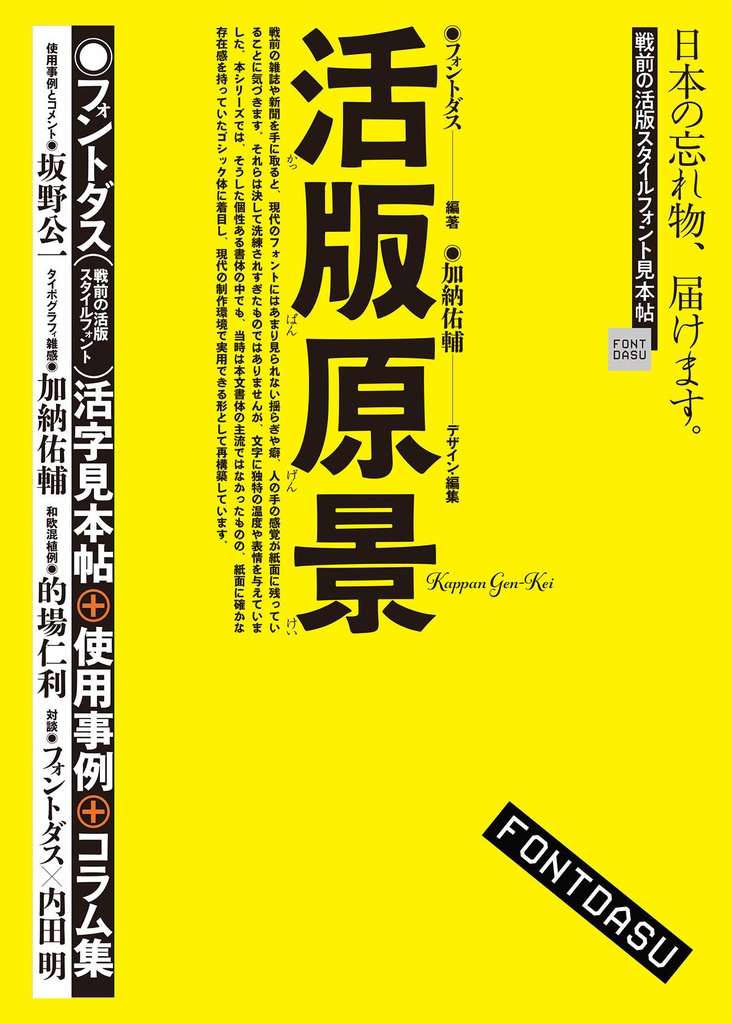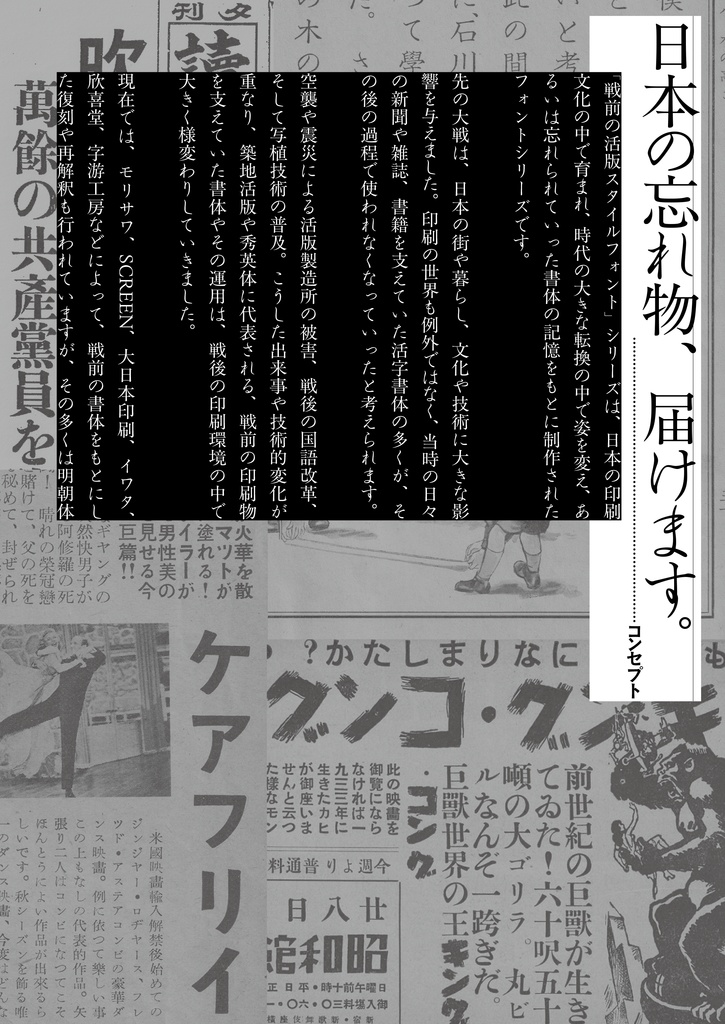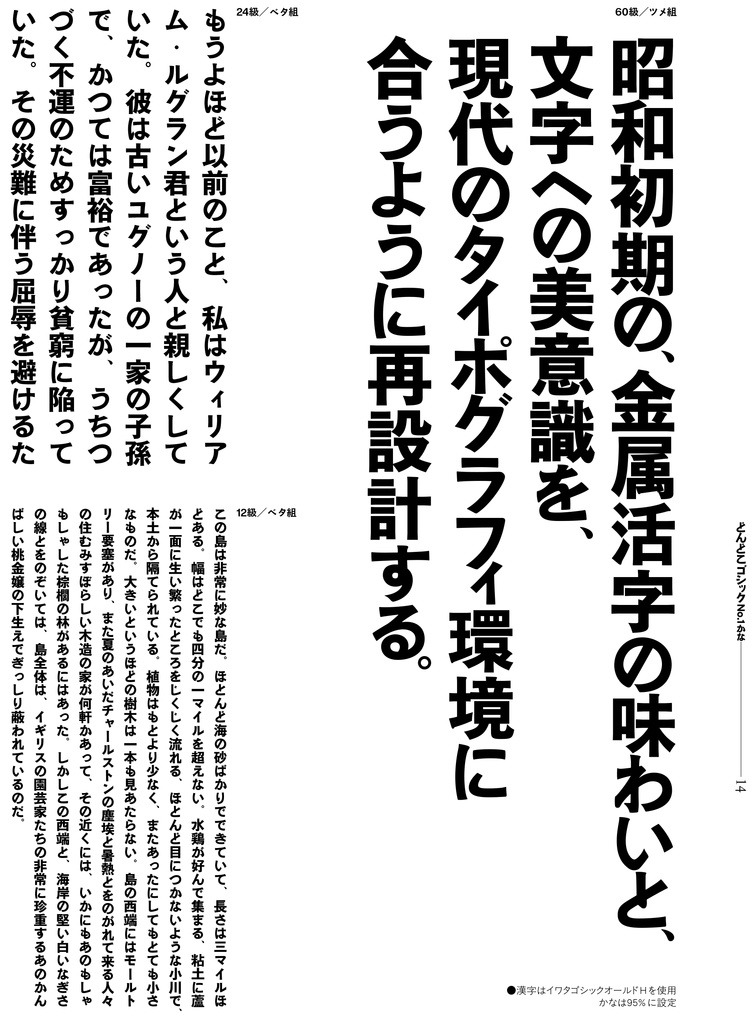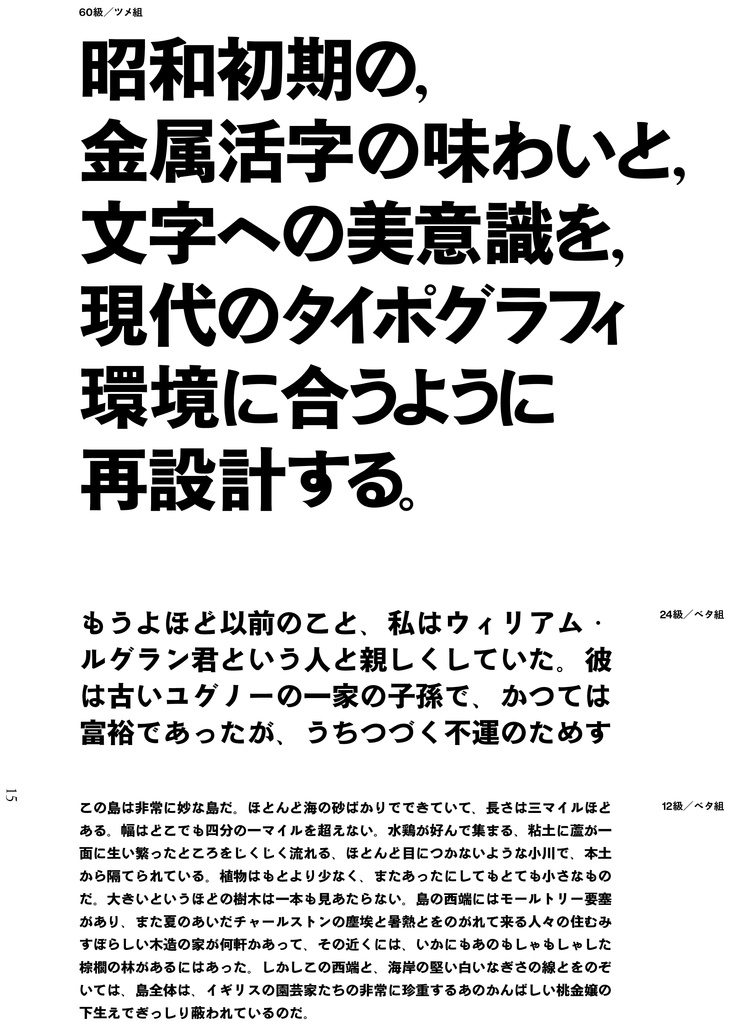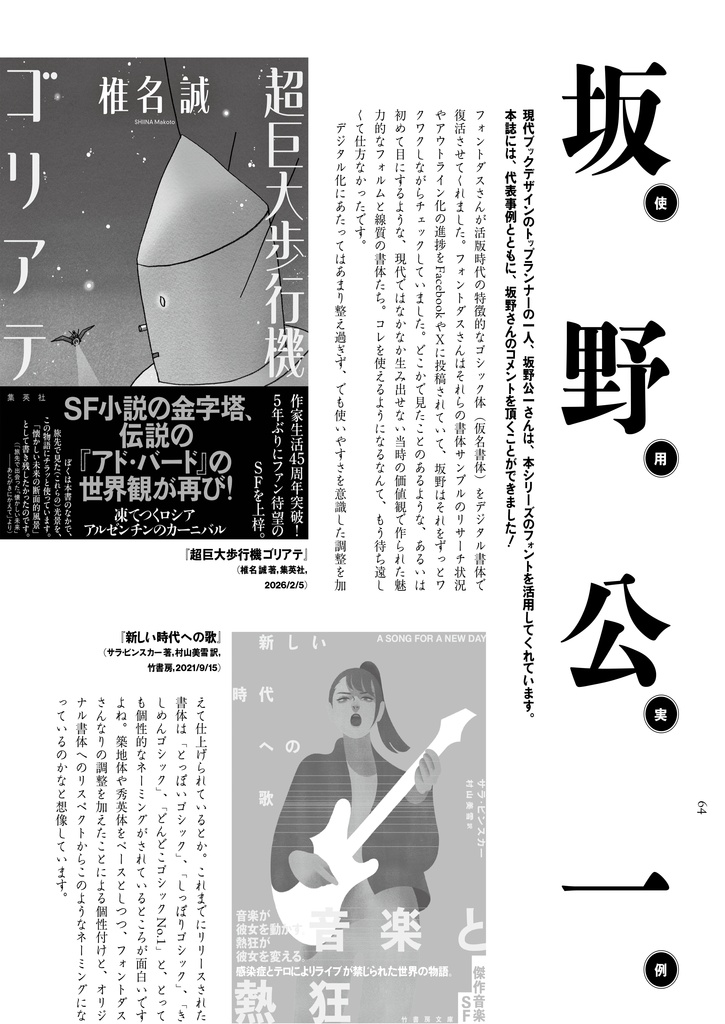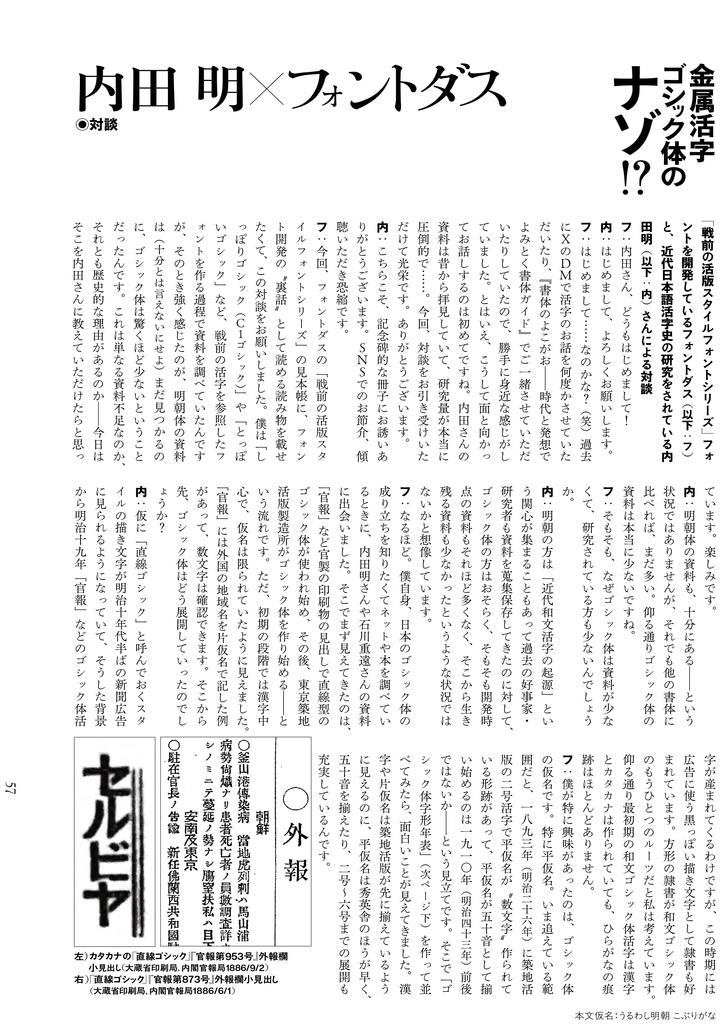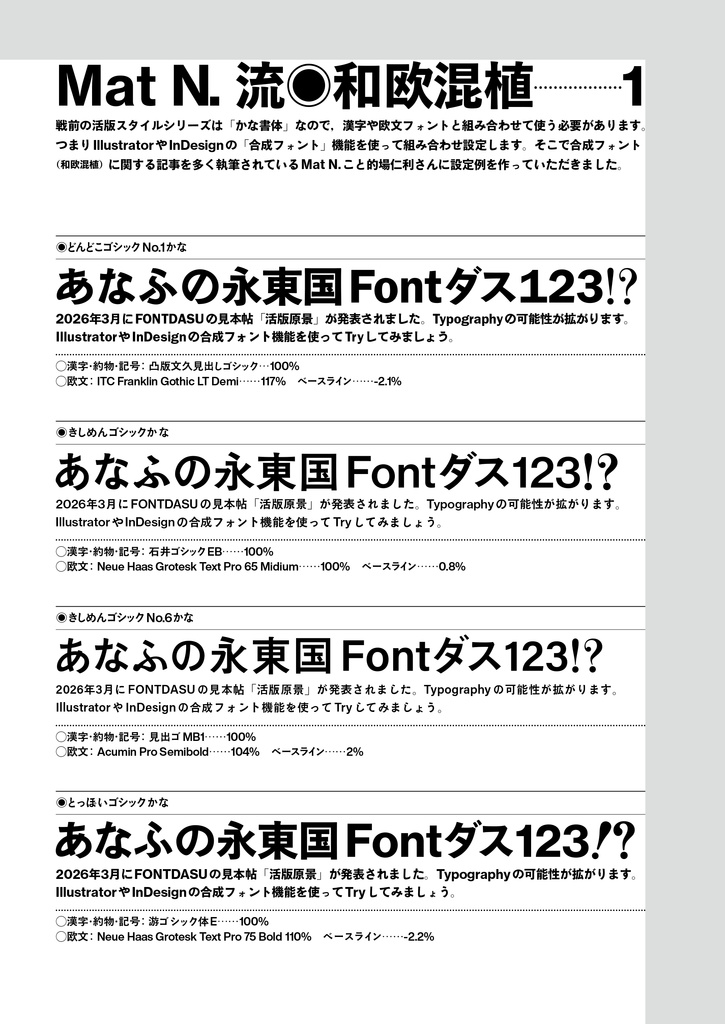
忘れられた活字の景色を、届けに来ました。 『活版原景』は、フォントダスが制作する 「戦前の活版スタイル」フォントシリーズの見本帳です。 字形だけでなく、背景・資料・使い方まで含め、 “読むためのフォント見本帳”として制作しています。 【収録内容】 ・フォント組版見本(縦組/横組) ・装幀家 坂野公一さんによる使用事例+コメント ・活字史研究者 内田明さんとの対談(戦前ゴシック体史) ・元ネタ資料/開発裏話 ・混植例(的場仁利) ・編集/デザイン:加納佑輔 【商品タイプ】 ■ 紙+PDFセット 冊子とPDFの両方が付属します。 ■ 紙版(冊子) 実際の紙と印刷で楽しむ見本帳です。 活版のニュアンスや組版の空気を、紙面で確認できます。 ■ PDF版(ダウンロード) スマートフォンやPCで閲覧できるデータ版です。 いつでもどこでも参照できます。 【仕様(紙版)】 ・サイズ:B5 ・ページ数:約68ページ ・表紙:表面カラー印刷/中面:モノクロ印刷 【注意】 ・本商品は書籍です。フォントデータは付属しません。 ・PDFの無断転載・再配布は禁止しています。